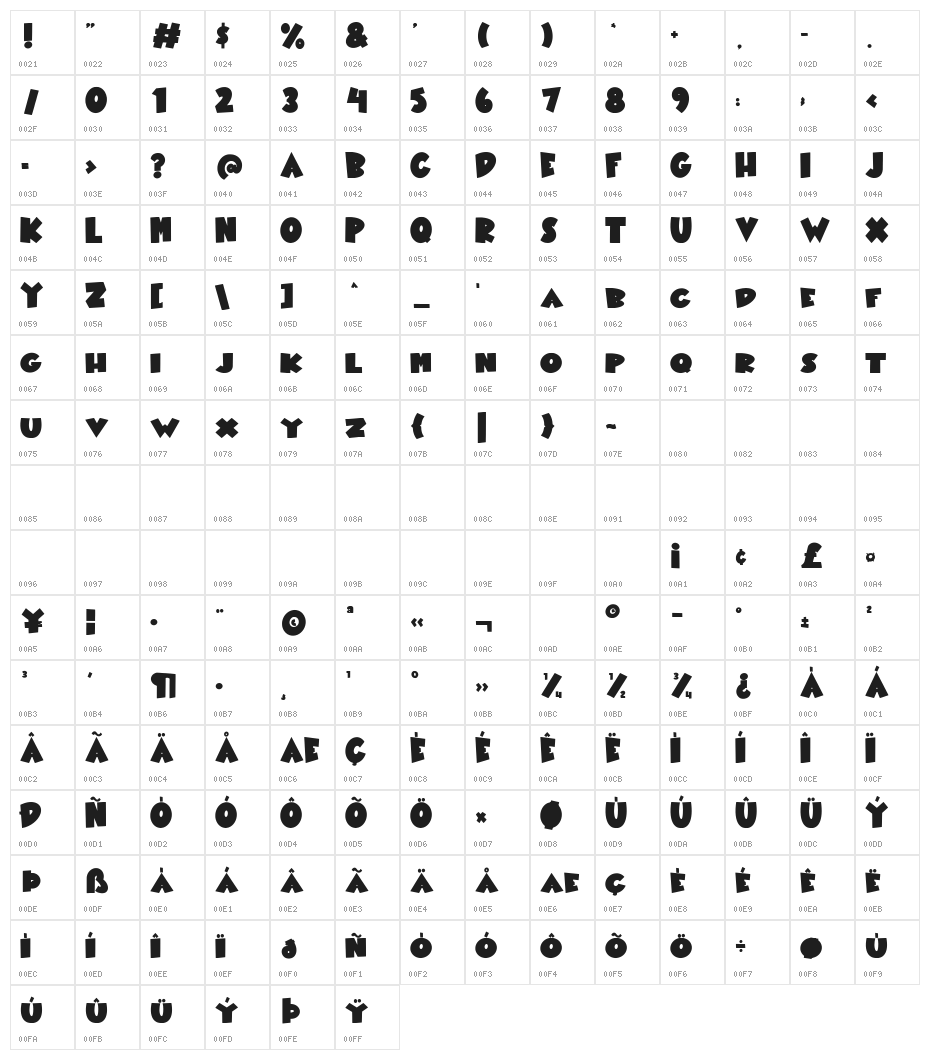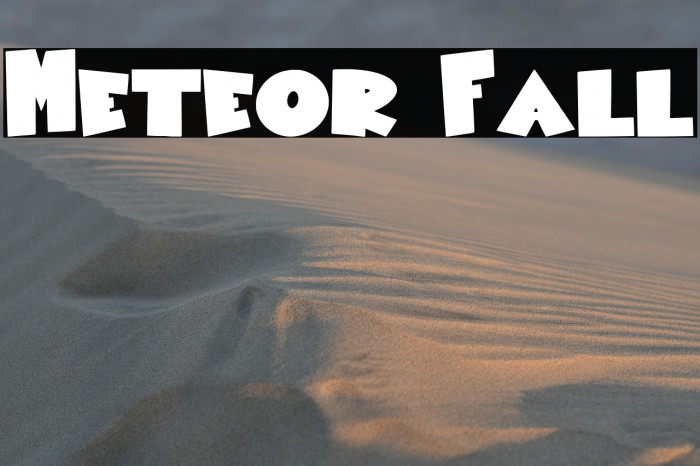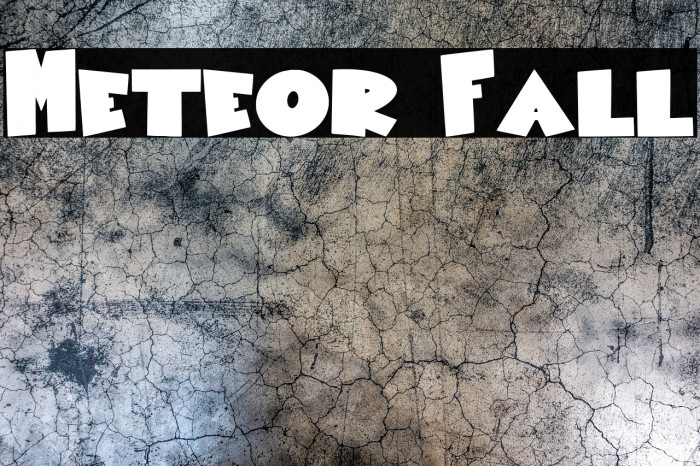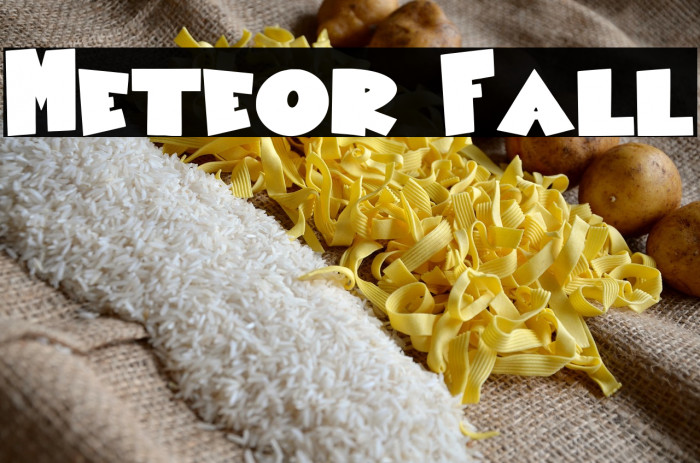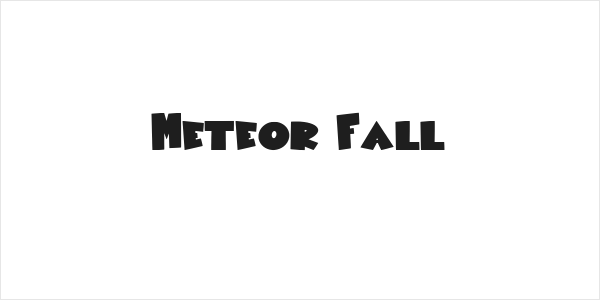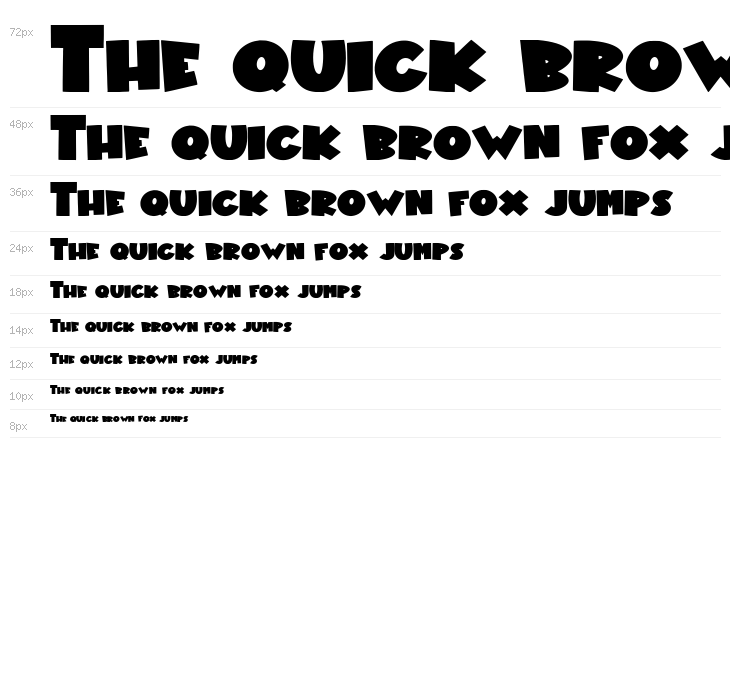
Meteor Fall Font
| Stile generale | Playful, Energetic |
| Caso d'uso | Headlines, Posters, Branding |
| Progetti proposti | Ideal for children's books, playful branding, event posters, and any project needing a fun, eye-catching typeface. |